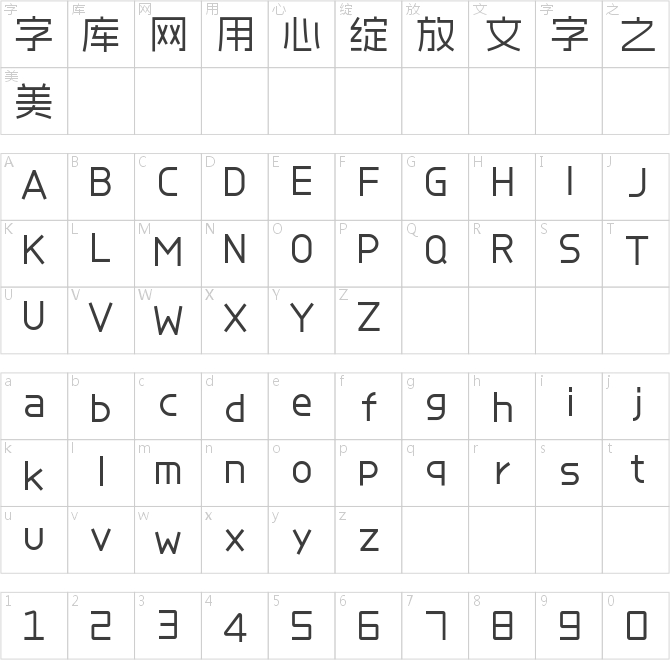
愛點風雅黑 詳情頁
﹤p﹥﹤span style="color: rgb(85, 85, 85)﹔ font-family: "﹔Microsoft YaHei"﹔, -apple-system, ui-sans-serif, system-ui, "﹔PingFang SC"﹔, Helvetica, "﹔Hiragino Sans GB"﹔, sans-serif, "﹔Noto Sans Nushu"﹔﹔ font-size: 15px﹔ text-align: justify﹔ text-wrap-mode: wrap﹔ background-color: rgb(255, 255, 255)﹔"﹥愛點風雅黑是廣州愛點視覺文化有限公司(愛點字庫)研發(fā)的商用免費字體,個人及企業(yè)可永久免費使用。該字體設(shè)計端正如砥、筆直如松,秀雅時尚,可免費用于各類廣告、UI設(shè)計用途。﹤/span﹥﹤/p﹥愛點風雅黑字體字庫是一款讓人賞心悅目、百看不厭的中文字體,適合各類廣告和產(chǎn)品包裝設(shè)計應(yīng)用,字體大小3.94MB,格式為ttf字體,上傳用戶是張茗緯,作者/版權(quán)方為愛點